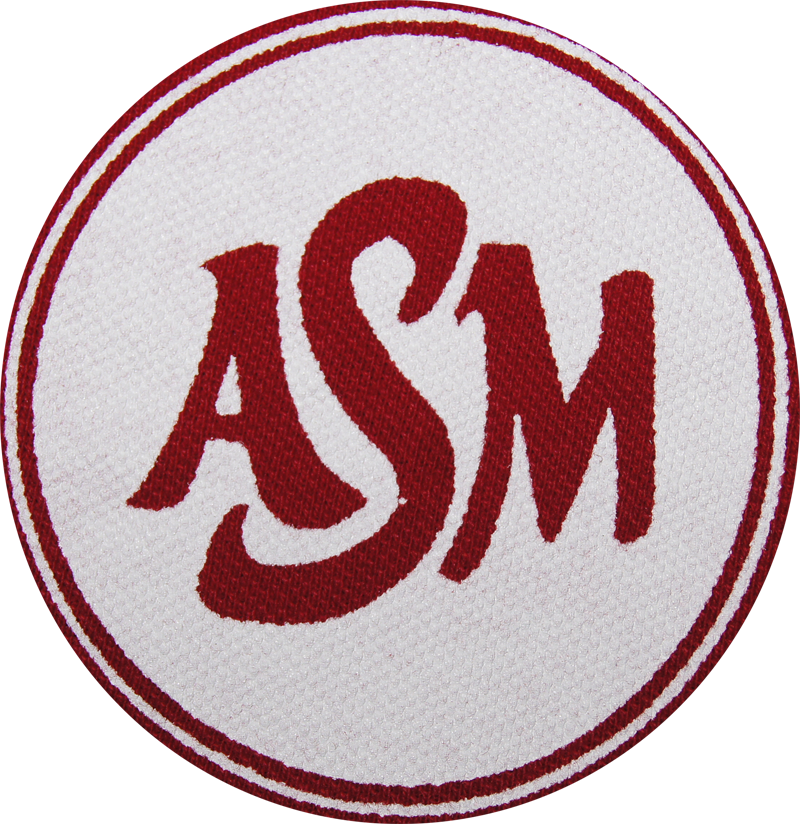
ASM - Suche Font … Bitte un Hilfe!
bin auf der suche nach diesem font kann mir da wer behilflich sein bitte....dankeasmnetz_zpsdeccf9dc.png
So wie die Buchstaben aufeinander abgestimmt sind, vermute ich mal, dass es sich um ein eigens gezeichnetes Logo handelt und nicht um eine normale Satzschrift. Sollte doch eine Satzschrift Pate stehen, dann wurde diese mit großer Wahrscheinlichkeit für das Logo individuell modifiziert. Brauchst Du genau diese Schrift oder wären auch ähnliche Vorschläge hilfreich?
also aus meinem bisherigen informationen ist des wohl ne schriftart aber sicher bin ich da natürlich nicht...hmm